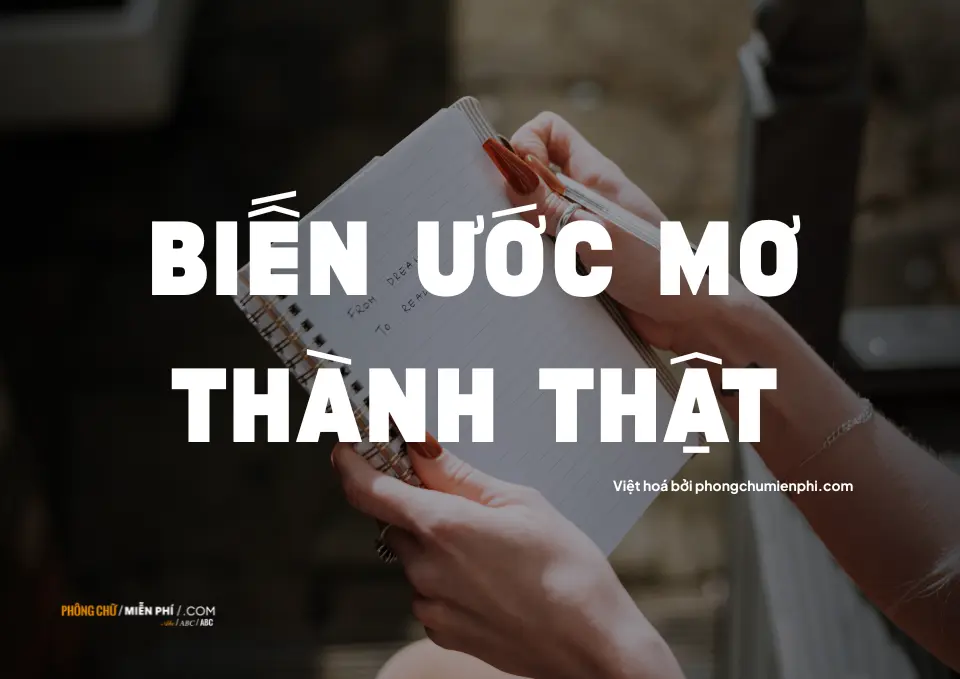
MEDIO VINTAGE là một font chữ sans serif đa năng mang đậm phong cách vintage cổ điển. Với những đường nét độc đáo và khác biệt, font chữ Việt hóa này vừa tạo được dấu ấn riêng, vừa giữ được vẻ đẹp mạnh mẽ và trường tồn theo thời gian. Phiên bản Rough & Textured của MEDIO giúp bạn dễ dàng tạo hiệu ứng in ấn cổ điển mà không cần sử dụng hiệu ứng từ bên thứ ba, tiết kiệm thời gian hoàn thiện thiết kế.
Phông chữ miễn phí MEDIO Font bao gồm đầy đủ:
Chữ hoa và chữ thường
Số và dấu câu
Ký tự có dấu tiếng Việt (font chữ Việt hóa)
Với sự đa dụng và tính thẩm mỹ cao, MEDIO VINTAGE là lựa chọn lý tưởng cho các dự án thiết kế mang hơi hướng hoài cổ, từ poster, logo, bìa sách cho đến bao bì sản phẩm.